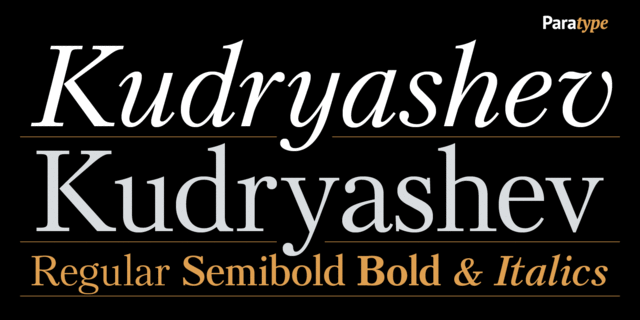
Текстовая гарнитура разработана в Отделе наборных шрифтов НПО Полиграфмаш в 1989 (дизайнер Любовь Кузнецова) на основе шрифта Литературная (Латинская) словолитного заведения Бертгольд (С.-Петербург), 1901, созданного на основе рисунков шрифта Lateinisch фирмы H.Berthold (Berlin), 1899.